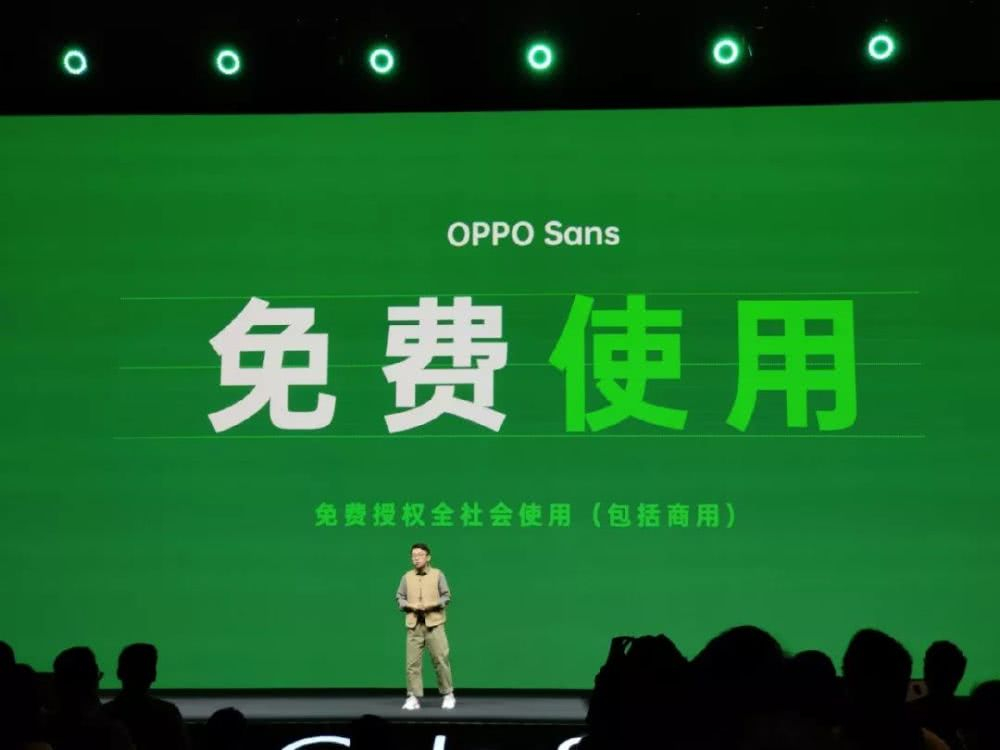
OPPO Sans 是 OPPO 全新品牌字體,首發於 ColorOS 6 操作系統,由 OPPO 與國內知名字體廠商漢儀合作開發出的全新中文字庫,總共 226003 個字節。
OPPO Sans 緊隨品牌升級的步調,用文字全方位探索科技美感,字體整體簡潔優雅,字型設計富有現代感,極具科技美感。
OPPO Sans(含中文及西文,6 款字重),字體採用全新骨架設計,中宮自然舒適,更加挺拔優雅;同時簡化筆畫,把握更多細節處理,去除出腳,使字體顯得更加乾淨。
簡潔富有變化的字體線條還融入 OPPO 產品曲線美學,極具現代感和未來感,字體更加現代,筆畫更加均勻,視覺表現更加整潔,非常適合用來作為設計素材使用,實用性相當廣泛。